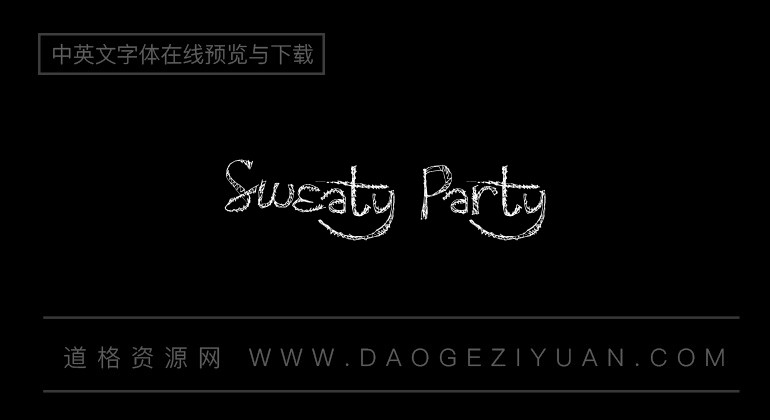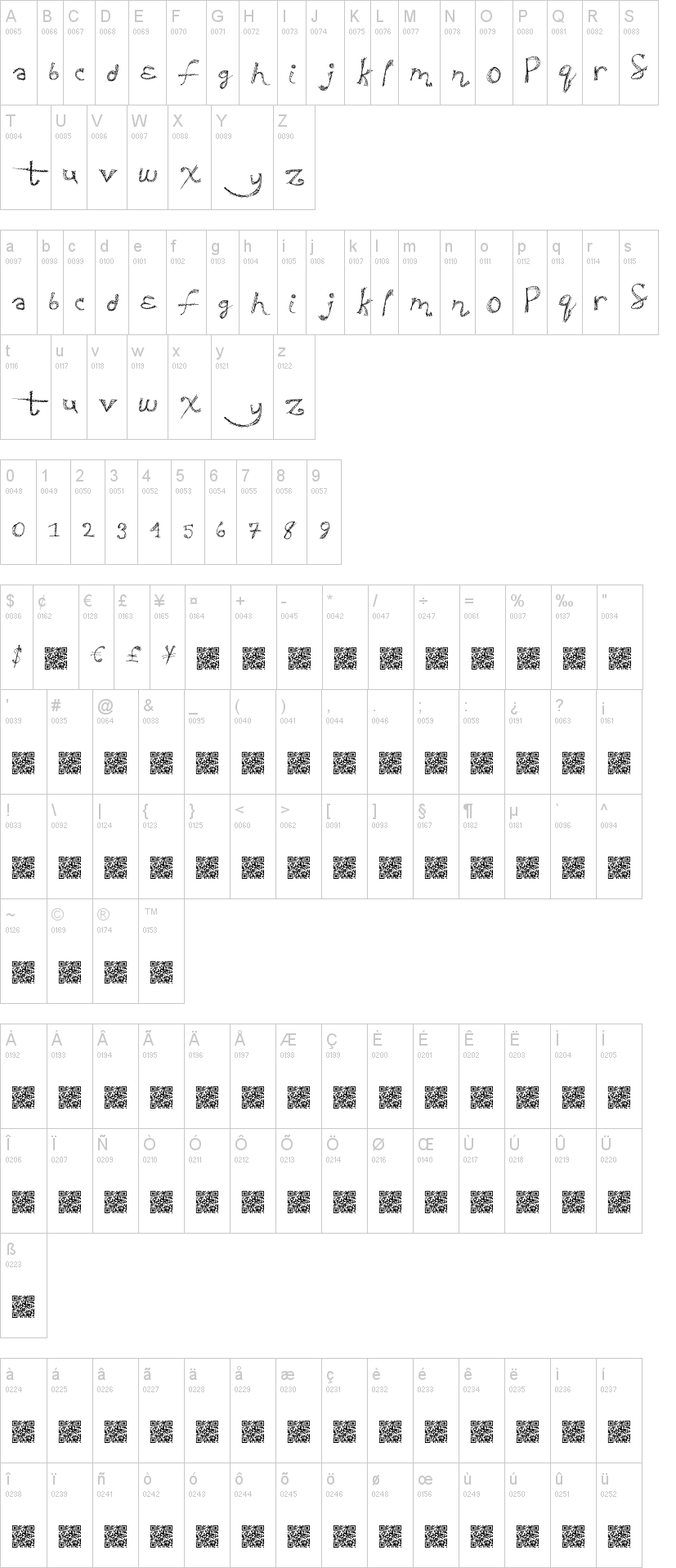
Sweaty Party 是一款卡通风格的手写字体,它具有轻松、活泼、可爱的特点,适合用于各种海报、T恤和卡片等设计中。这款字体的特点是每一个字母都有一个独特的设计,而且它的线条粗细不一,使用起来更加有趣。此外,它还具有自适应性,可以根据设计的主题和风格来改变字体的样式,以满足不同的需求。内容介绍
Sweaty Party是一款非常不错的手写艺术字体,具有很好的视觉感,适合于文化类的宣传设计、商业类品牌的广告和产品包装设计以及个性化文字排版等较多场景。